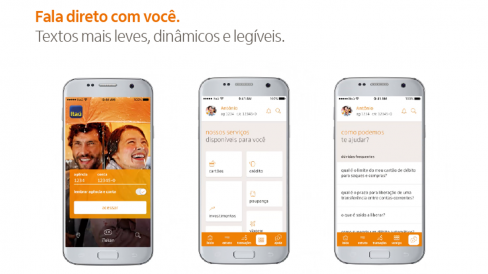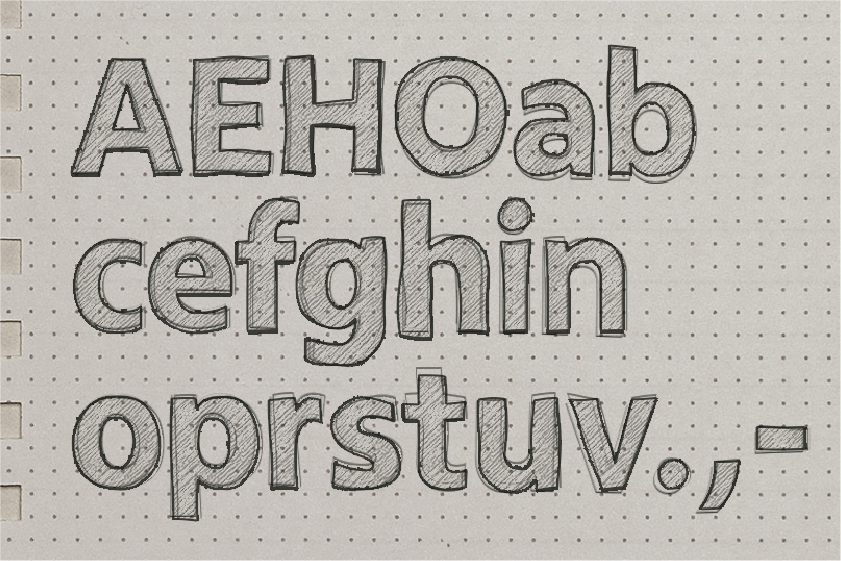
Itaú lança sua própria tipografia em todos os materiais do banco
Banco segue a linha de diversas empresas que estão apostando em tipografias únicas
O Itaú é mais uma empresa que aposta na criação de sua própria tipografia para consolidar uma imagem única à marca. O banco mudou sua tipografia, apostando em uma fonte leve e versátil, como diz o próprio vídeo de divulgação.
Criada pela área de Design do banco em parceria com a empresa inglesa Dalton Maag, a nova fonte já está sendo usada em todos os materiais do banco, inclusive nos aplicativos, e transmite atributos como consistência, eficiência e força, pensados especialmente para a construção da marca.
A fonte leva o nome do banco e foi pensada a partir da necessidade de ter uma fonte com características específicas para o mundo digital, sem perder de vista a aplicação nas demais mídias. “Prezamos por criar algo que transmitisse alta legibilidade, eficiência e redução de peso, sem perder os atributos que a fonte atual (Myriad) agrega para a marca, como proximidade, leveza e dinamismo”, explica Alexander Guazzelli, superintendente de Design do Itaú.
A tipografia exclusiva levou 10 meses para ser desenvolvida e começou a ser utilizada no final do ano passado, ,mas apenas em testes com a colaboradores do banco.
Recentemente, outras empresas também apostaram na criação de suas próprias fontes, como a Rede Globo e o Airbnb